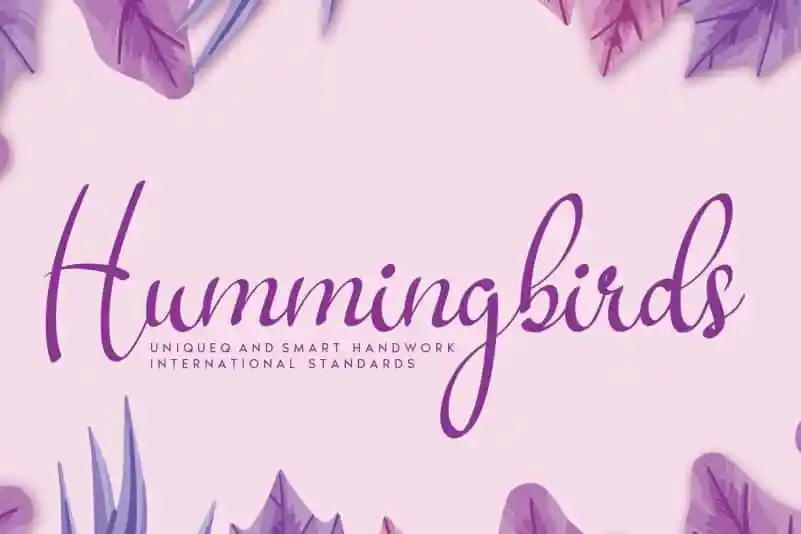
Hummingbirds Script Font – Fonte Grátis
Hummingbirds Script Font
A ‘Hummingbirds Script Font’ é uma fonte script criada com detalhes meticulosos e características únicas que permitem criar texturas efeitos de alta qualidade. Especialmente concebida para designers, artistas digitais e produtores de conteúdo que valorizam um toque único em seus projetos. Esta fonte é perfeitamente adequada para criações de design gráfico que exigem estilo elegante e sofisticado, seja ela para assinatura de produtos ou marcas. Ela oferece uma experiência única e inspiradora, transformando simples texto em elementos de arte vibrantes e distintivos. Seja você um artista digital criando efeitos especiais ou um designer gráfico buscando novas maneiras de expressar sua visão, a ‘Hummingbirds Script Font’ é uma escolha perfeita para se tornar parte da sua biblioteca personalizada de fontes. A ‘Hummingbirds Script Font’ foi desenvolvida pelo estúdio de arte digitais andikastudio e oferece um mix de elegância e criatividade, garantindo que a experiência de usar esta fonte seja tanto uma experiência visual quanto uma paixão para o design.